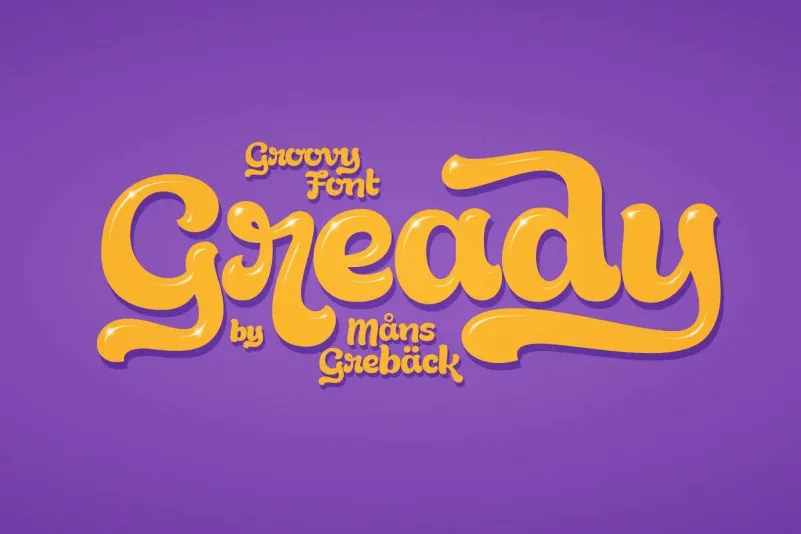
Esta fonte é inspirada no estilo moderno vintage e retro, combinado com a tradição americana antiga. Ela tem traços levemente ondulados e curvaturas divertidas, criando uma letra comic que transmite um caráter fluído e suave, além de uma personalidade gantry e otimista. Ideal para logos frescos e deliciosos como uma loja de sorvete ou uma loja de alimentos, também perfeita para headlines animadas ou qualquer contexto lúdico que ressoe com o lado criança dentro de nós. Este é um recurso gráfico divertido e estimulante, perfeito tanto para designers iniciantes quanto para aqueles com experiência.